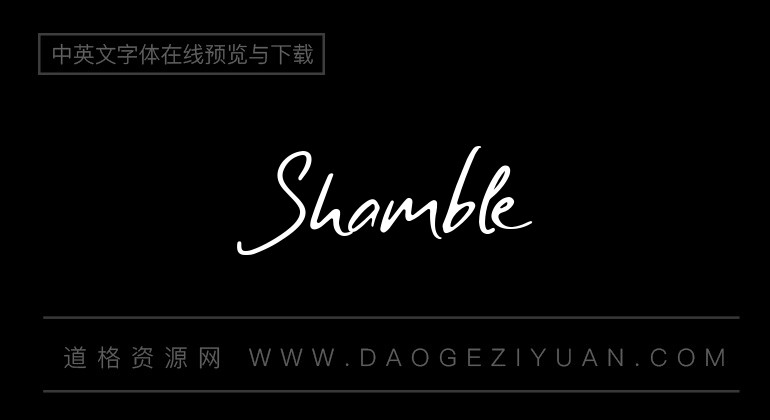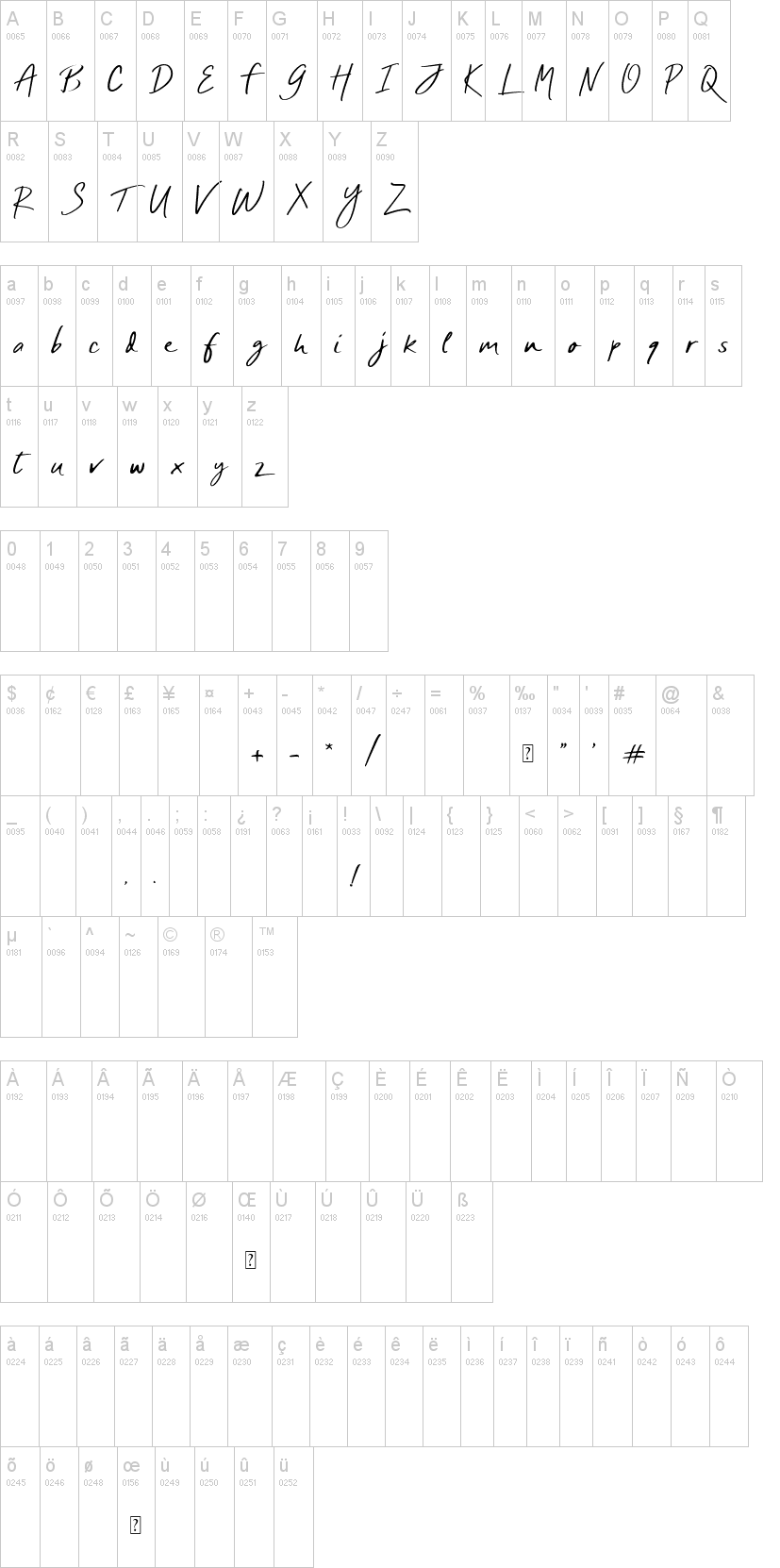
Shamble
Shamble 是一款多功能字体,由著名的英国字体设计师 Phil Garnham 创作。它是一款多功能字体,适用于任何项目,包括品牌、网站、印刷品、应用程序等。它具有清晰的外观,可以在任何尺寸的文本中使用。它的特点是拥有横向和纵向的设计,具有细节和多样性,可以在任何场景中使用。此外,它还具有全面的多语言支持,可以支持多种语言,从而使文字更加生动。
Shamble是一款非常不错的手写艺术字体,具有很好的视觉感,适合于文化类的宣传设计、商业类品牌的广告和产品包装设计以及个性化文字排版等较多场景。